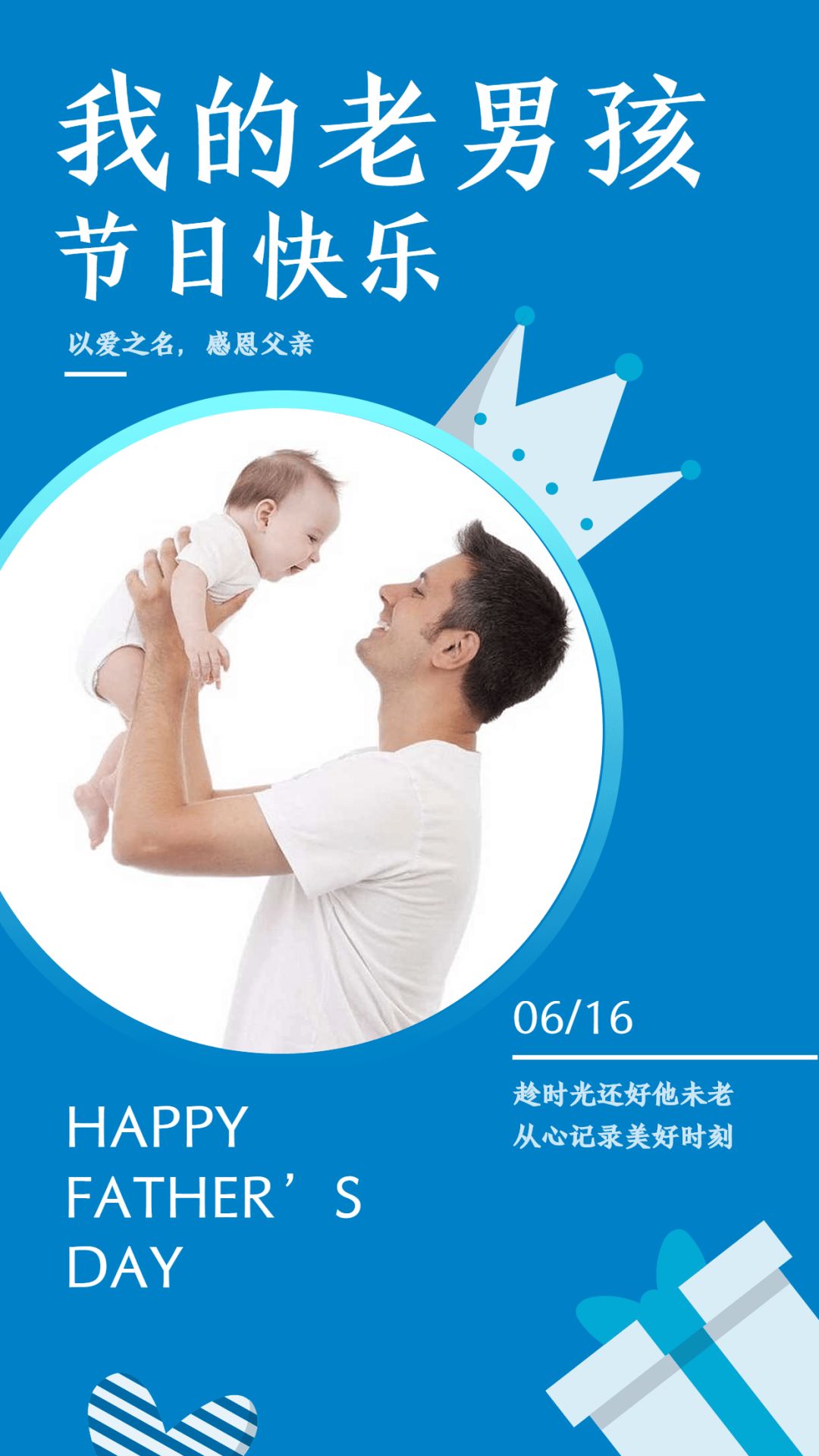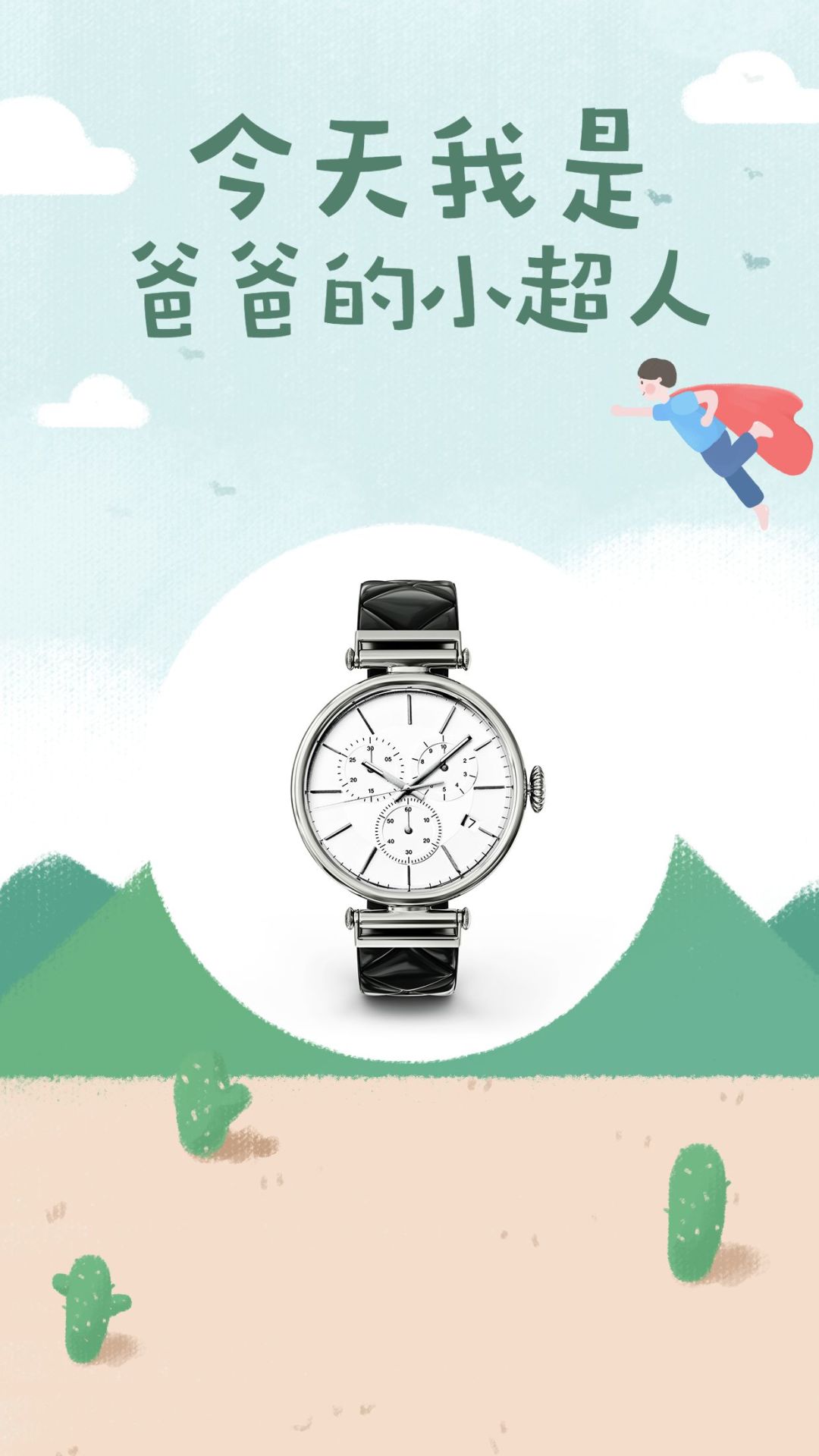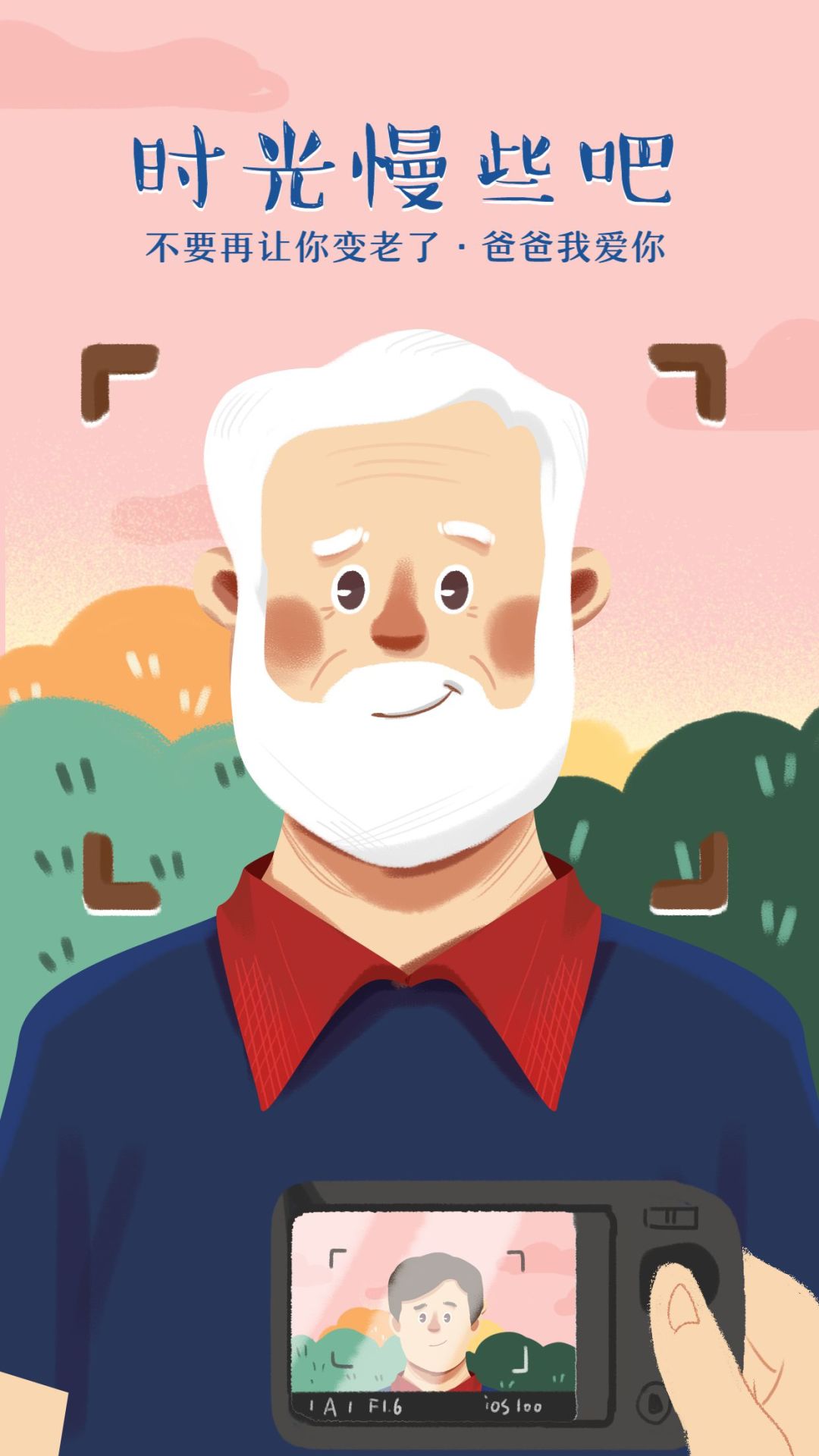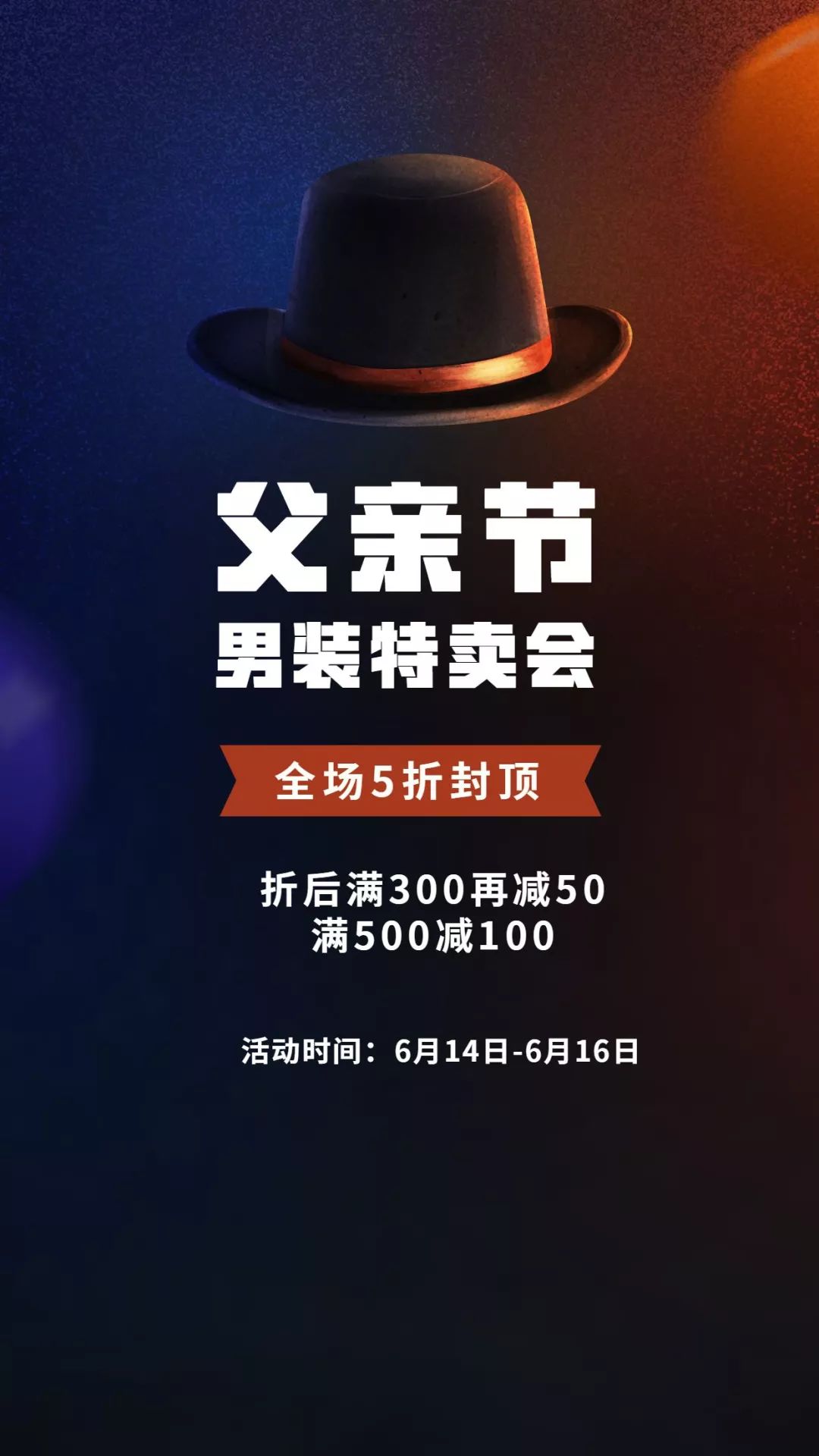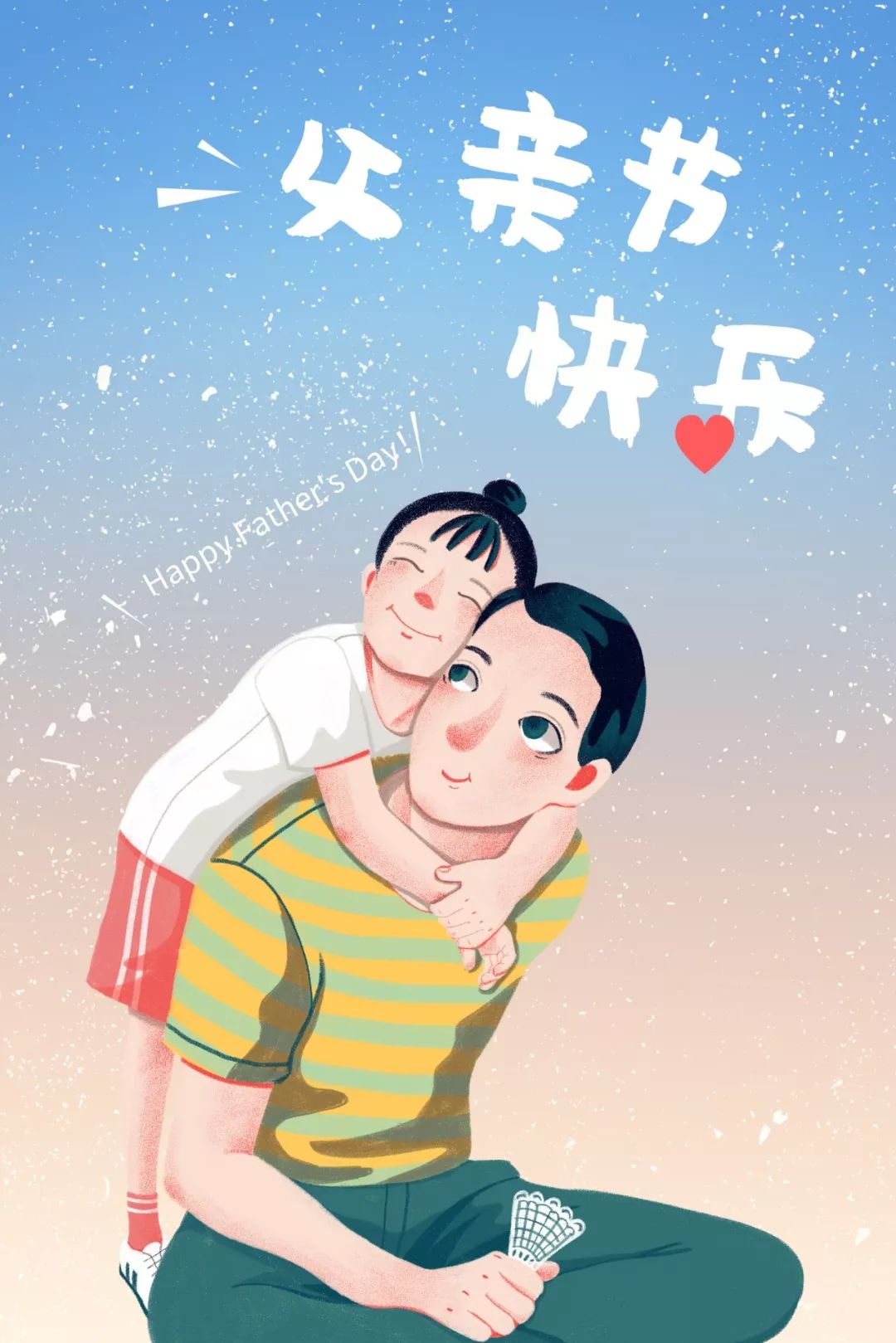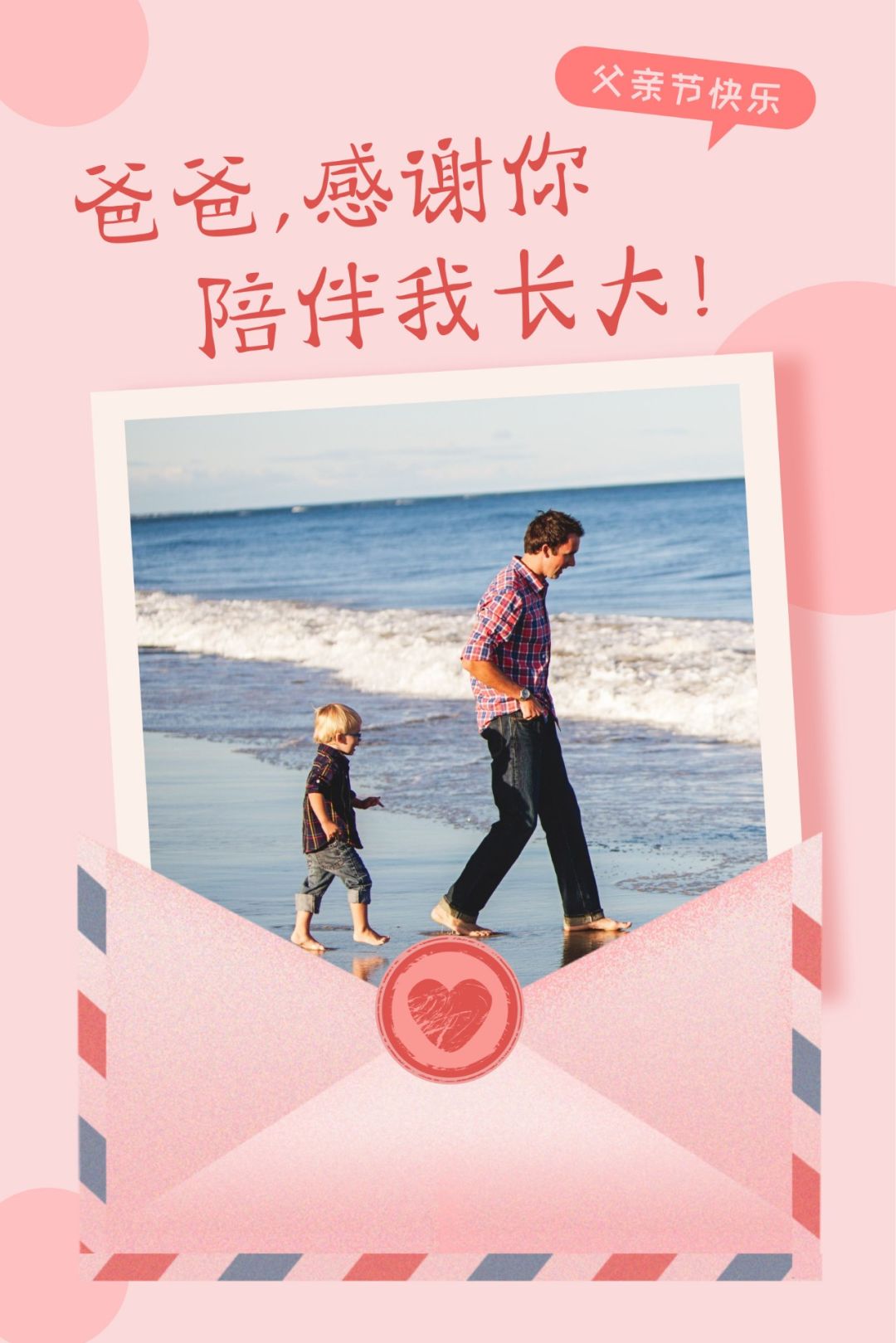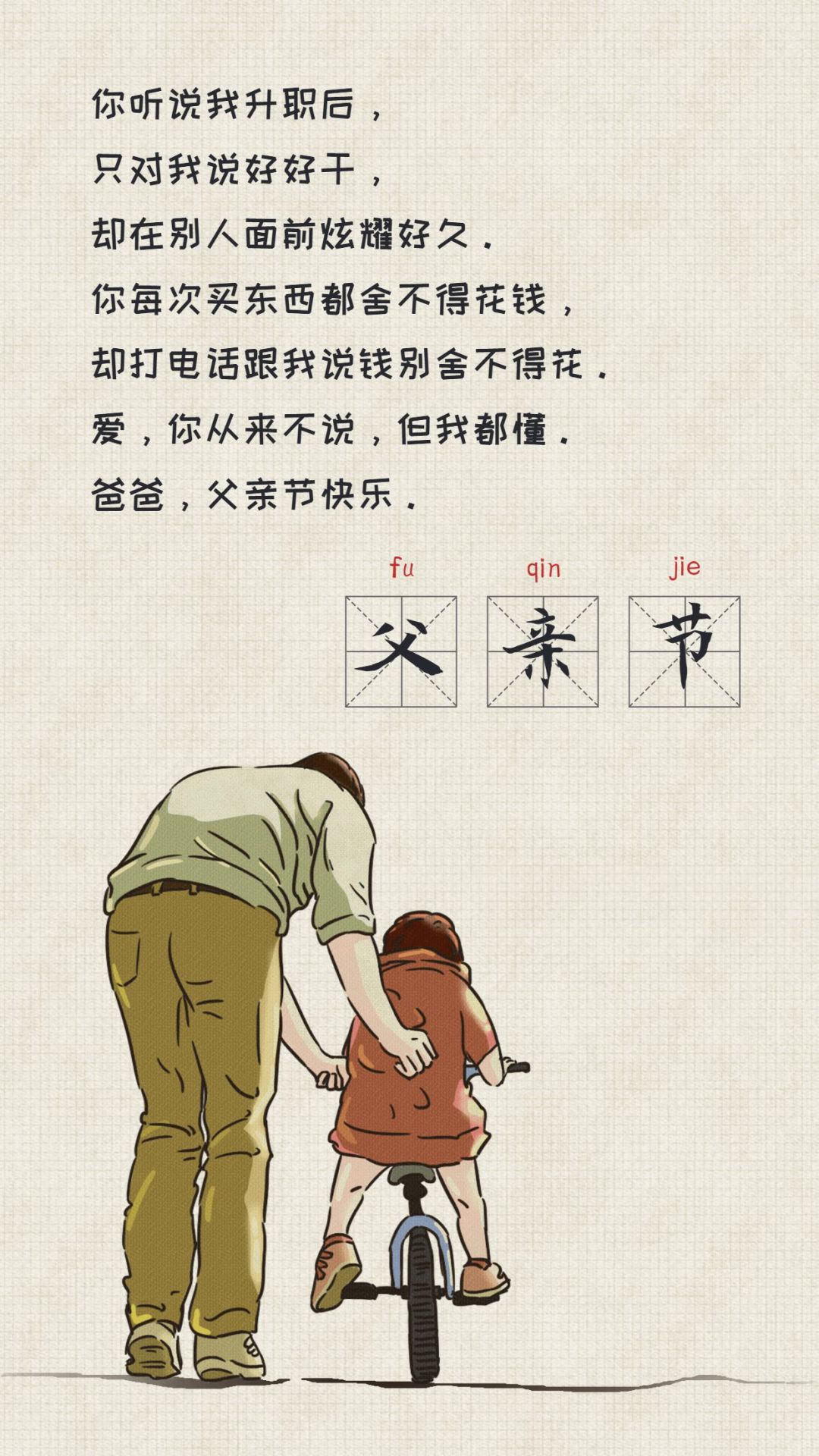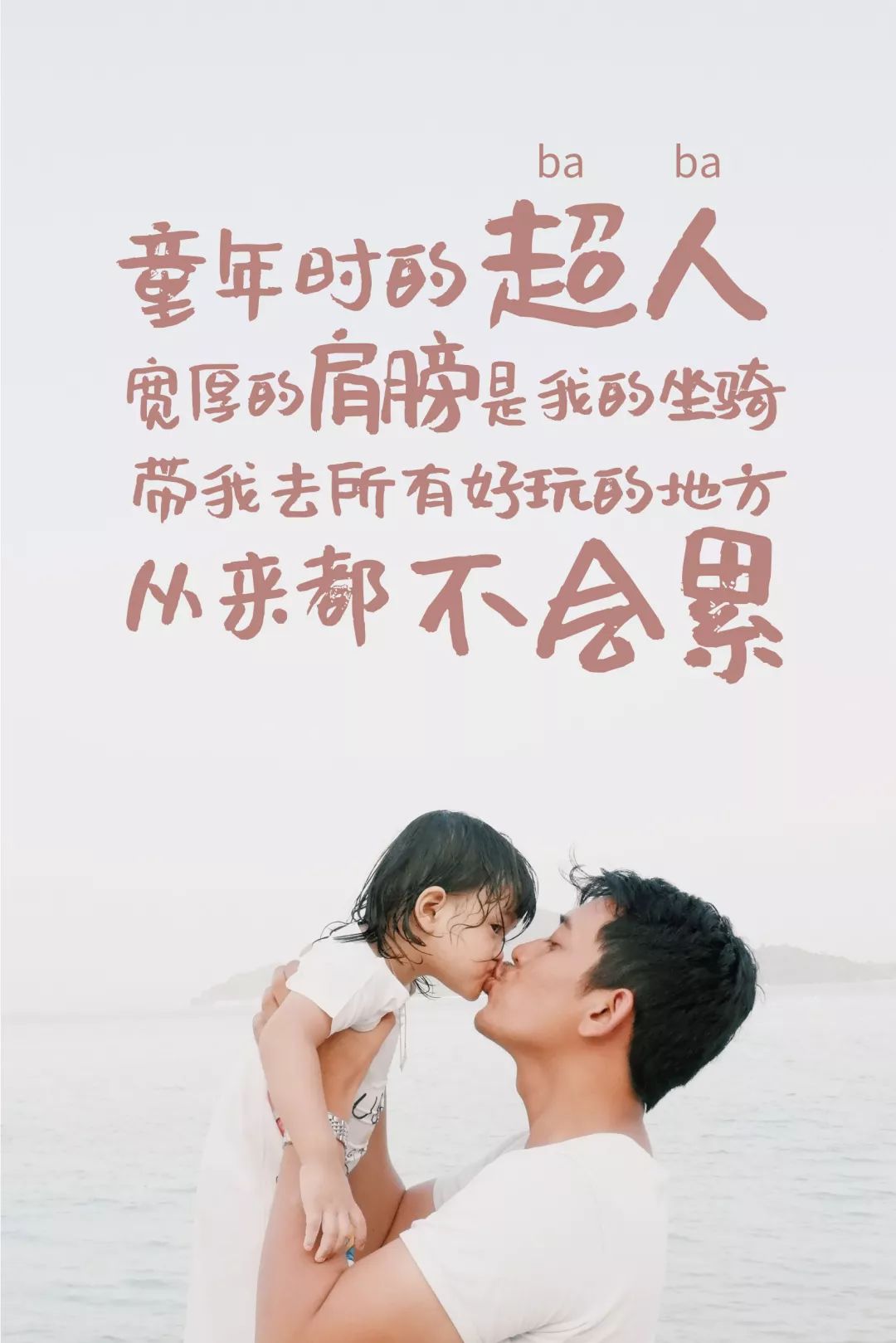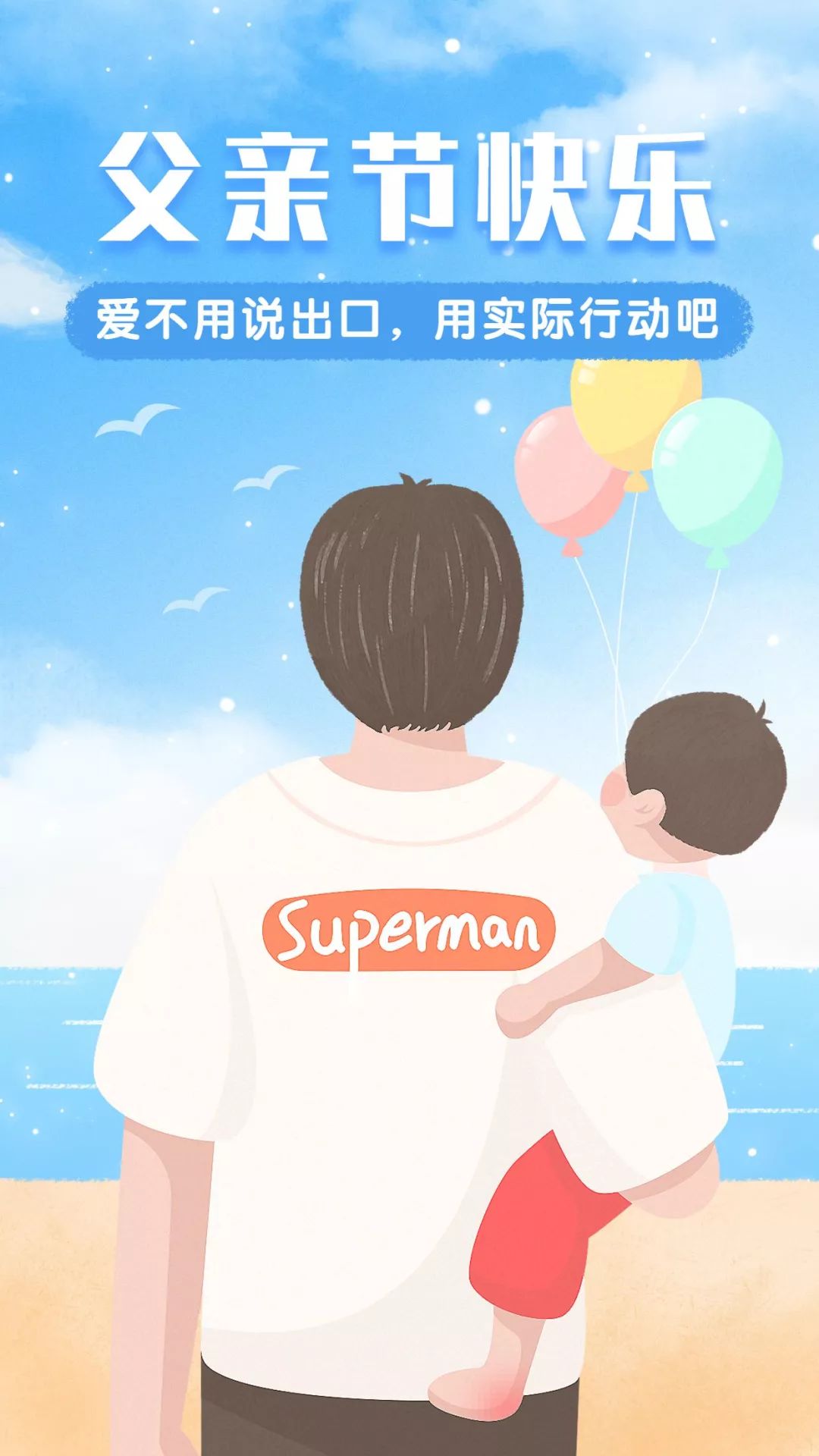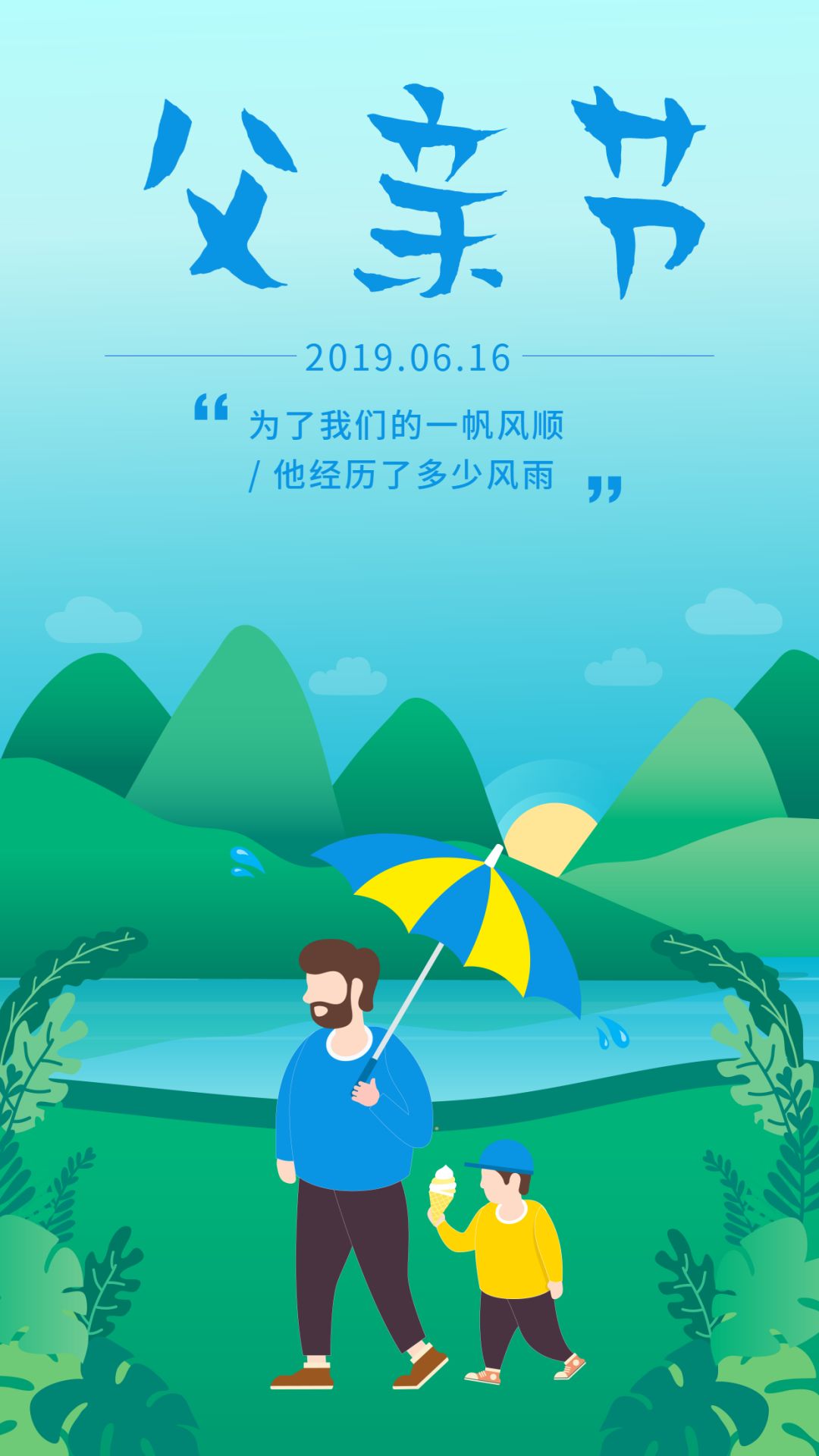
适合父亲节设计的字体分享,看看哪个字体更符合你想要的父爱
前几天柚子刚传了两张父亲节的字体案例,收藏量就猛增,看来大家对相关字体很有需求啊,毕竟妈妈是正面的爱,而爸爸更多的是背后的爱……
那今天就来对号入座,看看哪个字体更符合你想要的父爱~
回忆牌
小时候,父亲就是你的游乐场,你在肩背上收获了全世界,所以也想用最童真的字体,穿越回过去~
▲汉仪铸字童年体
▲汉仪六字黑
▲汉仪铸字木头人
▲沐瑶软笔手写体
▲站酷快乐体
▲汉仪小麦体
▲汉仪尚巍小时候
▲汉仪大圣体
▲汉仪跳跳体
▲汉仪新蒂黑板报
霸气牌
长大后,你觉得父亲是个英雄,什么都难不倒,其实他只是想在你面前足够强大,做个好榜样。
▲汉仪超级战甲
▲汉仪劲楷
▲庞门正道标题体
▲汉仪力量黑
▲汉仪铸字超然体
▲汉仪黑方
佛系牌
当你开始成家立业,父亲却渐渐老去,你很想留住时光,多陪陪心中的老男孩~
▲汉仪闫锐敏行楷
▲贤二体
▲汉仪雪君体
▲汉仪张乃仁行书
▲汉仪颜楷
▲汉仪南宫体